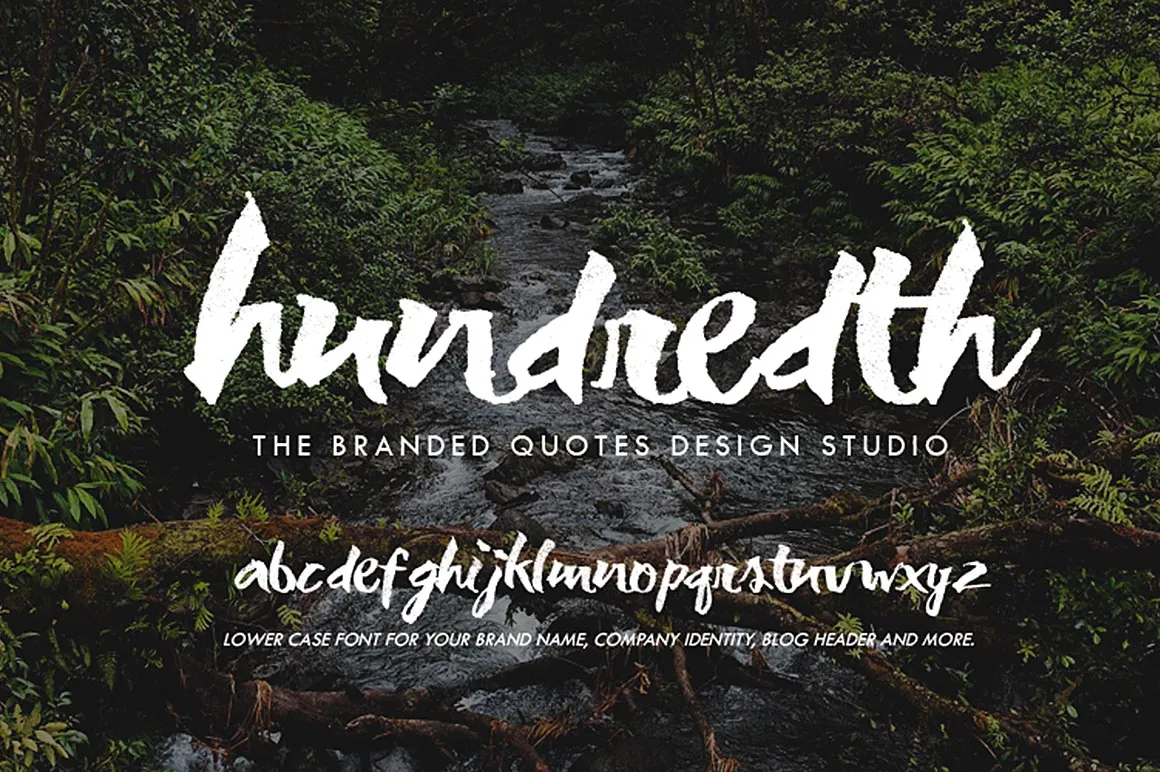
A Hundredth Font é uma fonte brush que traz a essência do estilo grunge com uma graça única. Ela vem diretamente dos designers de Hamilton, conhecidos por suas criações únicas e vibrantes. Esta fonte oferece um toque casual e interessante aos textos, ideal para personalizar notícias, anúncios ou qualquer tipo de texto que deseja destacar. É perfeito para quem busca algo moderno e atemporal ao mesmo tempo, uma combinação de estilo grunge com brilho contemporâneo. Se você procura por uma fonte que combine o charme da autenticidade do grito com a sofisticação do estilo grunge atual, então esta Hundredth Font é definitivamente para você. Não hesite em baixar e experimentar seu próprio texto personalizado usando essa fonte. Você vai adorar como ela dá um toque único aos seus projetos.